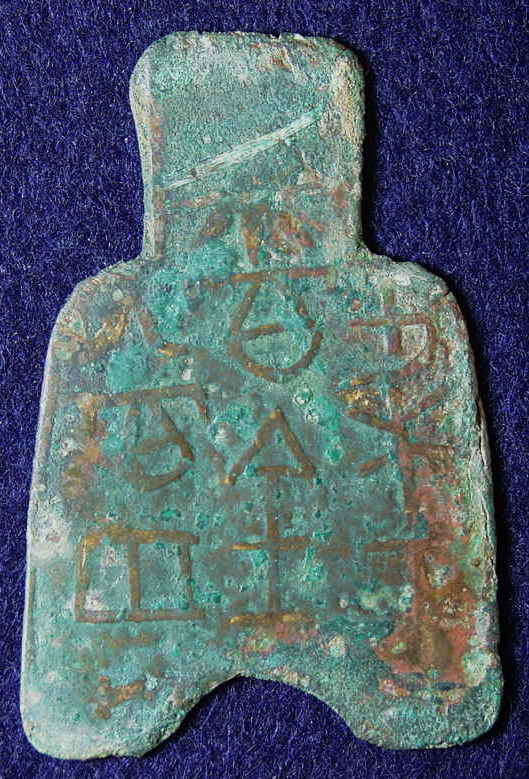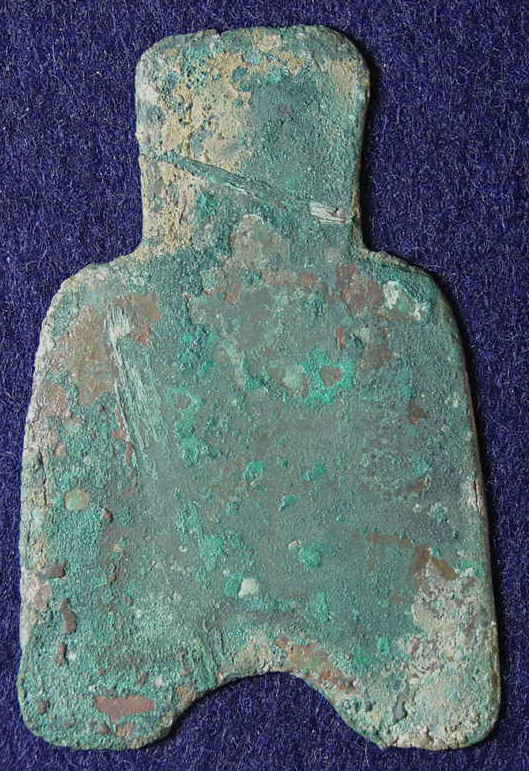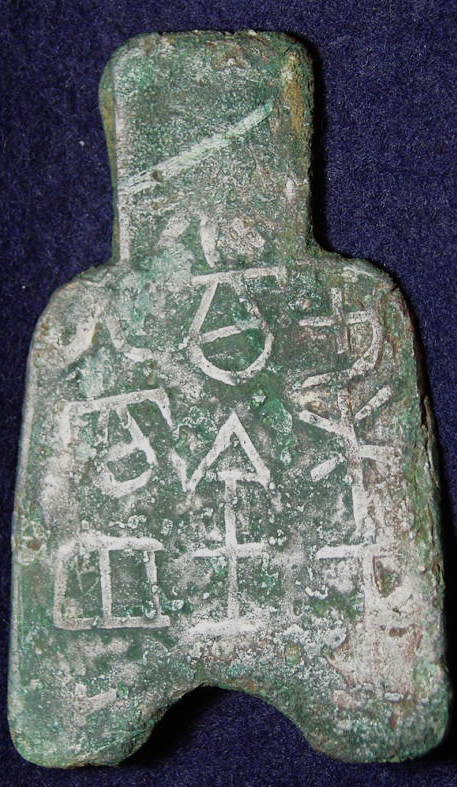
戦国貨幣・魏釿布3
文字/言語
漢字/漢語
材質/形態
銅/布銭
重さ
14.4g
大きさ
縦59.30mm、横39.74mm、厚さ1.14mm
中国戦国時代の魏国の貨幣。布銭と呼ばれるタイプのもの。 右に「梁正」、中に「尚百」、左に「當埒(土偏ナシ)」、あわせて「梁正尚百當埒(土偏ナシ)」と読む。
画像の3枚目はやや傾けて撮影したもの。